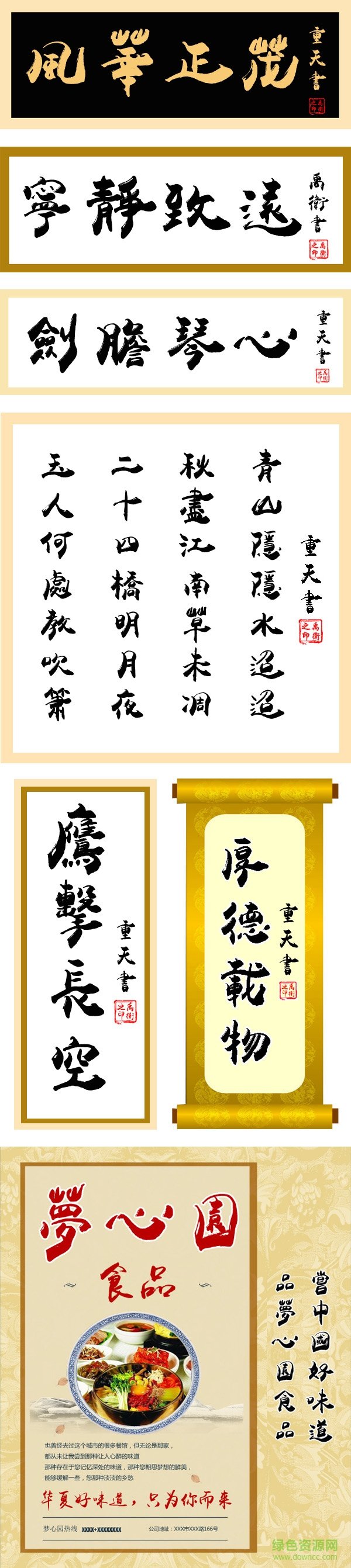
禹衛(wèi)書(shū)法隸書(shū)繁體是禹衛(wèi)先生寫的一款PC繁體隸書(shū),禹衛(wèi)先生的字體一直有一種厚重凝實(shí)的感覺(jué),寫出來(lái)的字一撇一捺都有種隆重的古風(fēng)隸書(shū)的韻味,十分適合喜歡隸書(shū)和喜歡厚實(shí)書(shū)法的朋友使用。喜歡的小伙伴快來(lái)綠色資源網(wǎng)下載吧!